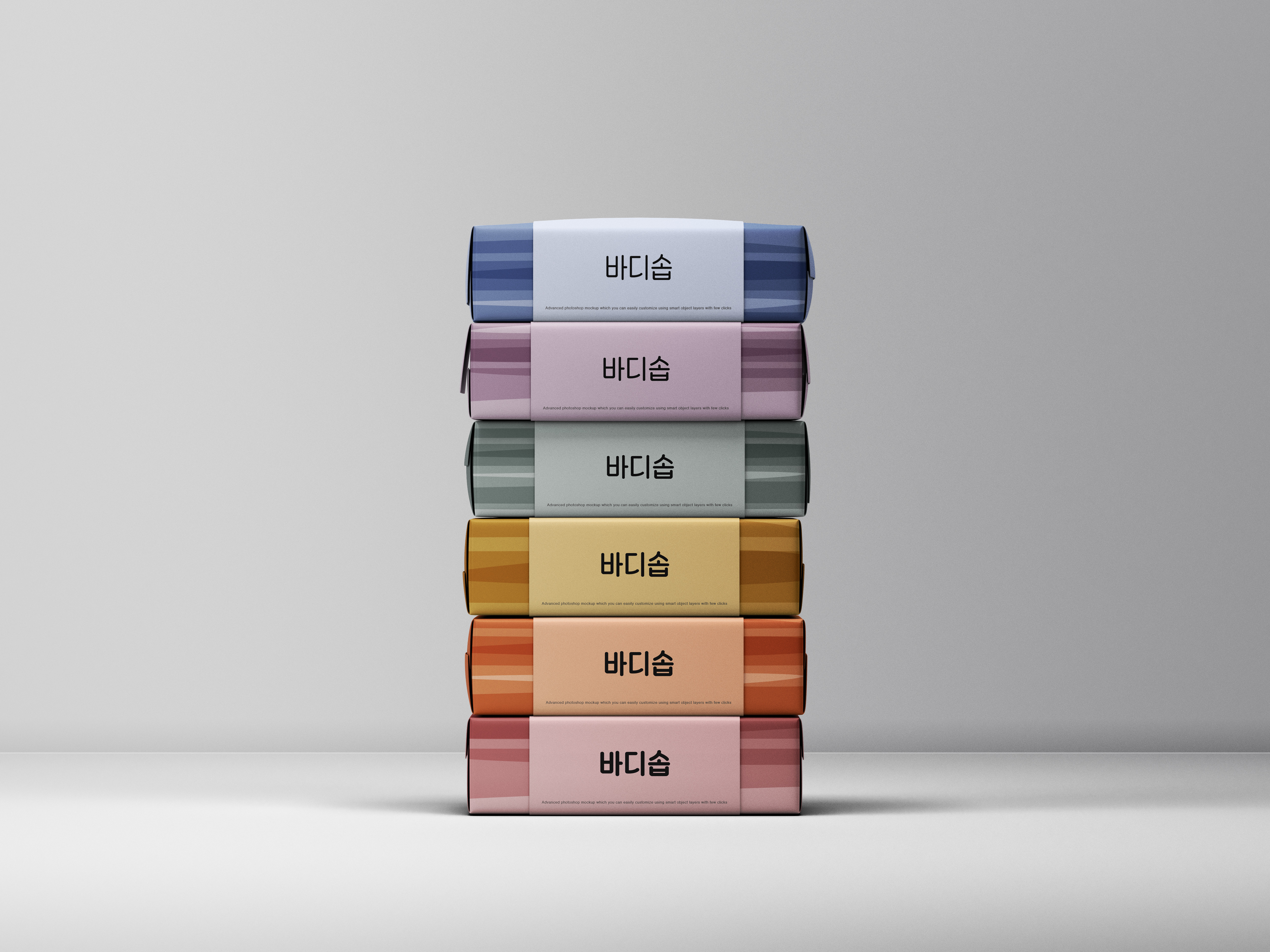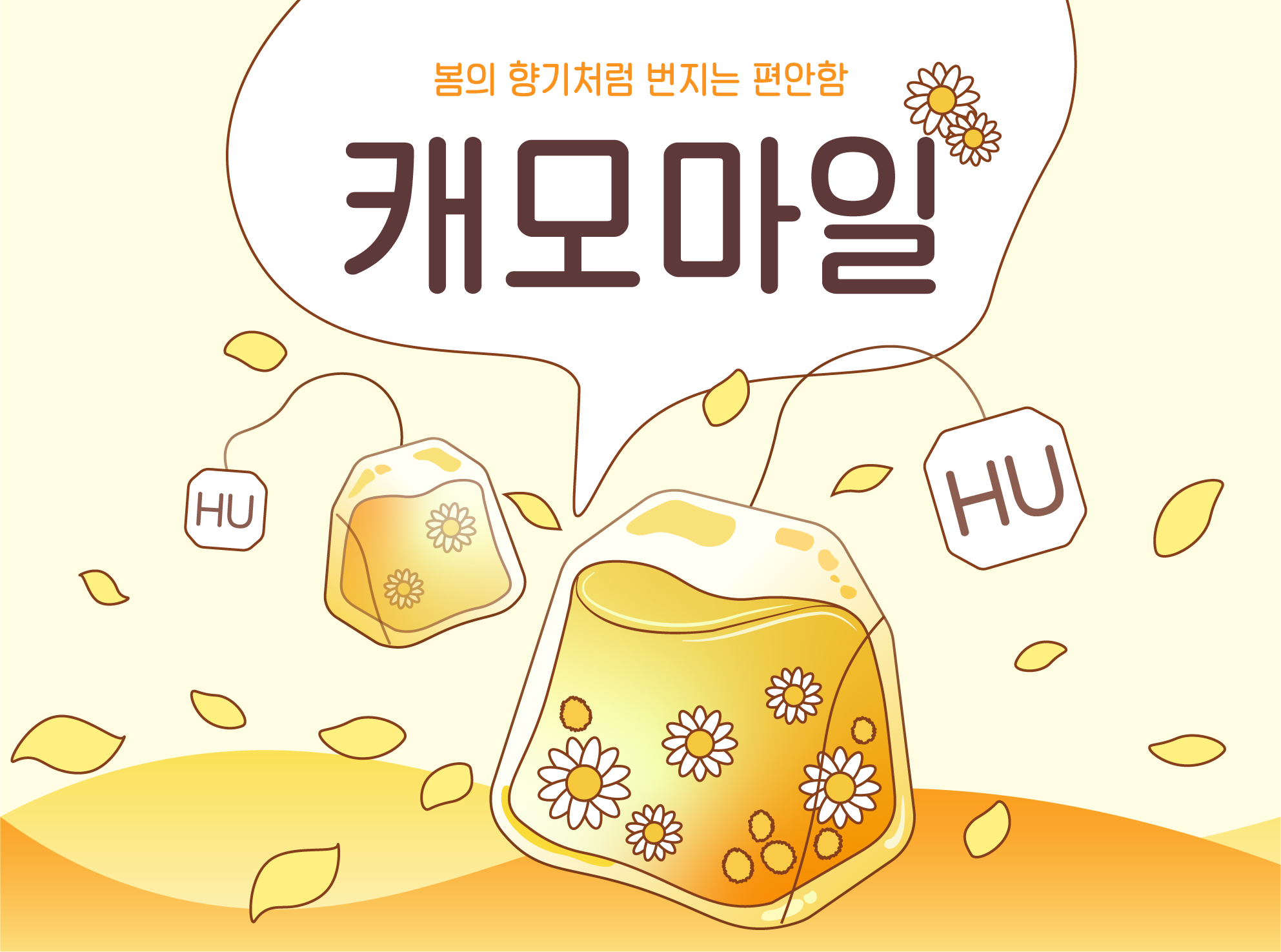
레트로한 분위기의 굴림체로 현대적인 자소와 획으로 재해석하였습니다.
또한, 자소의 크기가 시원시원하게 제작되어 가독성이 높습니다!
폰트      HU캐모마일 패밀리
굵기      6종
*  캐모마일 Light
(구수한 보리차와 동일 굵기)
* 캐모마일 Regular
* 캐모마일 Medium
* 캐모마일 SemiBold
* 캐모마일 Bold
* 캐모마일 ExtraBold
구성      KS한글 11,172자